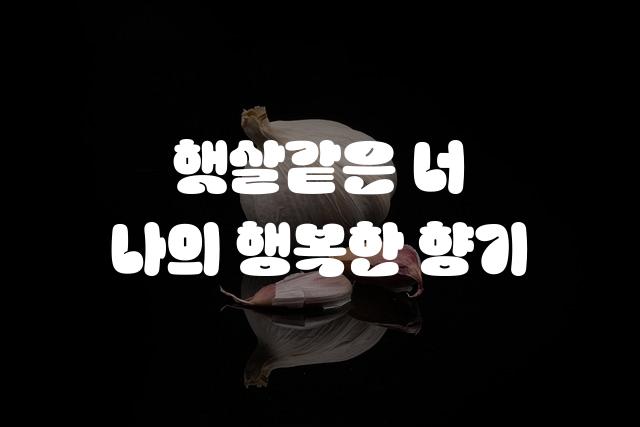
리아체는 롯데GRS에서 제작한 제목용 고딕 폰트로, 두꺼운 글자체와 독특한 디자인이 특징입니다. 강렬하면서도 꽉 찬 느낌을 주어 시각적으로 강한 인상을 남깁니다.
기본 고딕, 두꺼운 스타일, 굵은 고딕, 단단함, 길고/크고 계열의 생김새를 가지고 있으며
로고 디자인, 포스터, 광고 캠페인 등에서 자주 활용되며, 효과적인 메시지 전달에 적합합니다.
이 폰트는 광고/마케팅, 크리에이티브, 패션/뷰티 분야에 잘 어울리며,
세련된, 창의적인, 고급스러운 느낌을 담고 있는 것이 특징입니다.